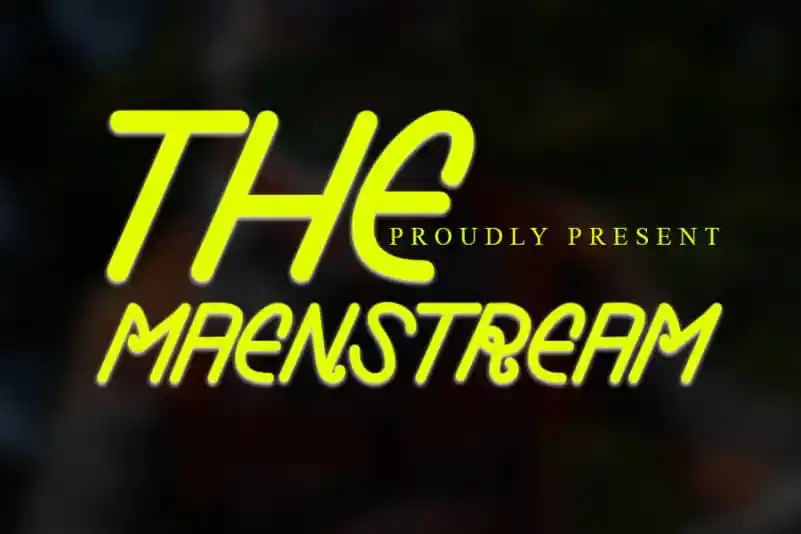
The Maenstream Display Font – Download Grátis
A fonte The Maenstream Display Font é uma escolha inteligente para quem busca estilo moderno em sua tipografia. Com seus influências clássicas e linhas retas, essa fonte manterá seu design elegante enquanto se mantém atual e fresco. Suas variações únicas atendem a um amplo leque de ideias criativas, desde assinaturas e títulos até papelaria. Seja você um designer de revistas ou uma marca inovadora, The Maenstream Display Font oferece as ferramentas necessárias para criar designs distintos e modernos em qualquer aplicação. Engane-se apenas sobre o que a fonte já traz naturalmente bela e versátil.